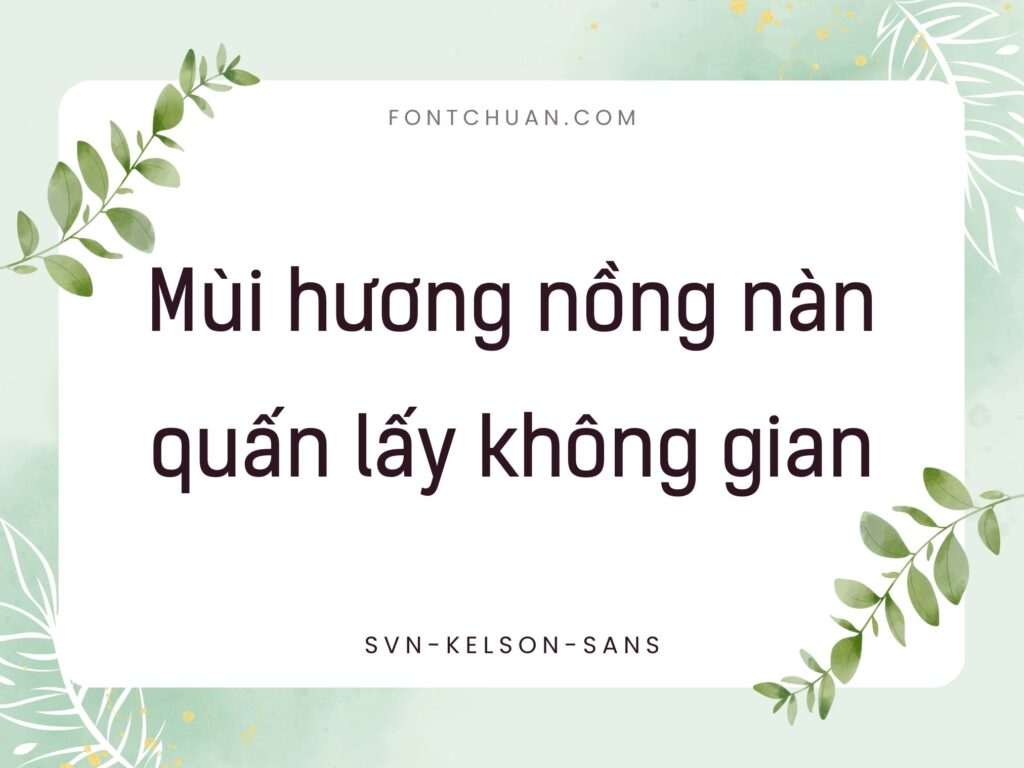
Font SVN Kelson Sans Trọn Bộ Việt Hóa
Tác giả Font: Bruno Mello
Font SVN Kelson Sans là phiên bản Việt hóa của kiểu chữ Kelson Sans, được thực hiện bởi STYLEno.1 Fonts. Kelson Sans là một kiểu chữ sans-serif hiện đại, được thiết kế bởi Bruno Mello từ São Paulo, Brazil. Font này là phiên bản cải tiến của họ chữ Kelson gốc, mang đến sự tối giản và thanh lịch trong thiết kế. Kelson Sans bao gồm ba trọng lượng: Light, Regular và Bold, với đầy đủ các ký tự chữ hoa, chữ thường, chữ số và dấu câu, hỗ trợ đa ngôn ngữ. Với thiết kế đơn giản nhưng tinh tế, Kelson Sans phù hợp cho nhiều mục đích sử dụng như thiết kế logo, tiêu đề, bao bì sản phẩm và các ấn phẩm truyền thông.
SVN Kelson Sans lý tưởng cho các dự án thiết kế yêu cầu sự hiện đại và tối giản, như thiết kế logo thương hiệu, tiêu đề tạp chí, bao bì sản phẩm và các ấn phẩm truyền thông. Các ngành nghề như quảng cáo, giáo dục và công nghệ có thể tận dụng font này để tạo điểm nhấn trong thiết kế. Ngoài ra, font cũng thích hợp cho các sự kiện như Tết, Giáng sinh, Valentine và các lễ hội khác.